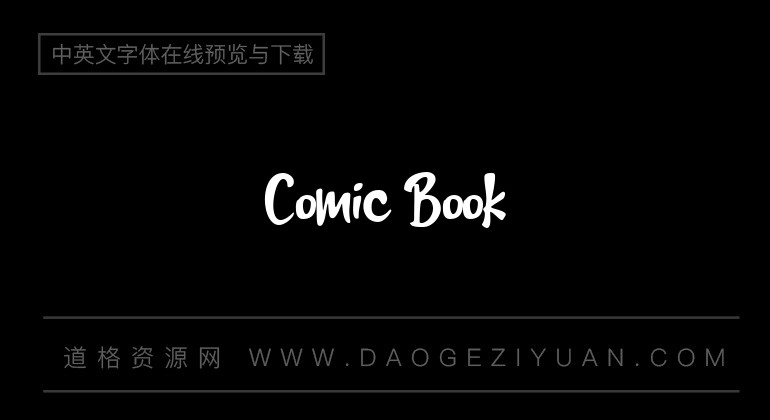
Comic Book 字体是一种常用的漫画字体,它具有浓重的漫画风格,并且是一种易读的字体,适用于漫画、游戏、海报等多种场景。它具有粗犷的外观,搭配出色的排版,可以使文字更加有趣、生动、有趣。它的字体风格较为复古,比较适合用来制作漫画、游戏、海报等多种场景。内容介绍
Comic Book是一款非常不错的手写艺术字体,具有很好的视觉感,适合于文化类的宣传设计、商业类品牌的广告和产品包装设计以及个性化文字排版等较多场景。